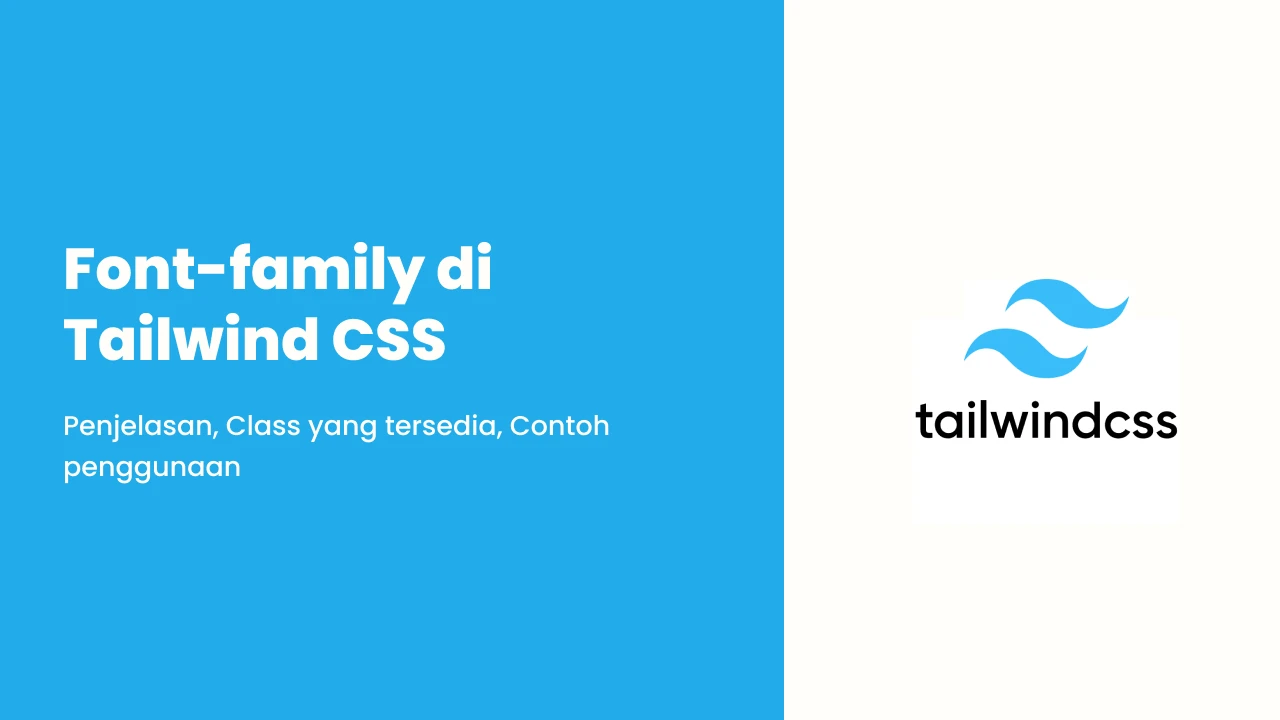
Apa itu font-family di Tailwind?
Font-family di Tailwind CSS adalah utilitas (class) yang dipakai untuk menentukan jenis huruf (font) yang digunakan pada elemen HTML.
Class-class yang tersedia:
font-sans
→ Menggunakan font sans-serif (huruf tanpa kait), seperti: system-ui, sans-serif, dsb.
font-serif
→ Menggunakan font serif (huruf ada kaitnya), seperti: Times New Roman, Georgia, dsb.
font-mono
→ Menggunakan font monospaced (tiap huruf lebarnya sama), seperti: Courier New, Consolas, dsb.
font-[nama-font]
→ Pakai font yang kamu tentukan sendiri.
font-(family-name:<custom-property>)
→ Pakai font dari CSS variable yang kamu buat sendiri.
Contoh Penggunaan:
berikut hasilnya:
Kalau mau pakai font custom:
berikut hasilnya:
Kalau pakai CSS Variable:
berikut hasilnya:
Responsive (Bisa beda font di ukuran layar tertentu)
Misalnya di layar kecil pakai sans, di layar besar berubah jadi serif:
berikut hasilnya:
Custom Theme
Kalau kamu mau atur font default Tailwind sendiri, kamu bisa setting di @theme
:
@theme {
--font-display: "Oswald", "sans-serif";
}
Lalu pakai di HTML:
berikut hasilnya:
Bisa juga nambahin pengaturan tambahan seperti:
Font Feature Settings (pengaturan fitur khusus di font)
Font Variation Settings (pengaturan variasi ukuran huruf)
Kalau Mau Pakai Font dari Luar (contoh Google Fonts)
@theme {
--font-roboto: "Roboto", sans-serif;
}
Singkatnya:
Class |
Fungsi |
font-sans |
Font gaya modern, tanpa kait |
font-serif |
Font gaya klasik, ada kaitnya |
font-mono |
Font lebar huruf sama semua |
font-[custom] |
Pakai font buatan sendiri |
font-(family-name:--variable) |
Pakai font dari CSS Variable |